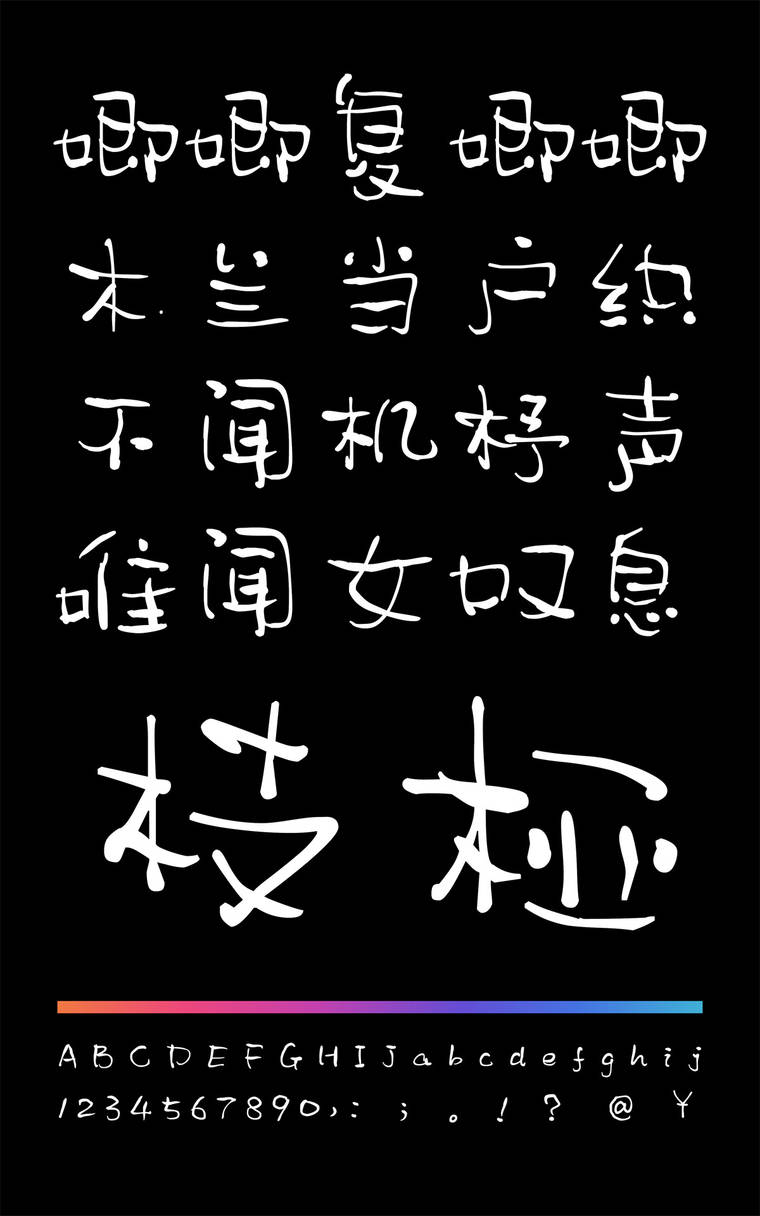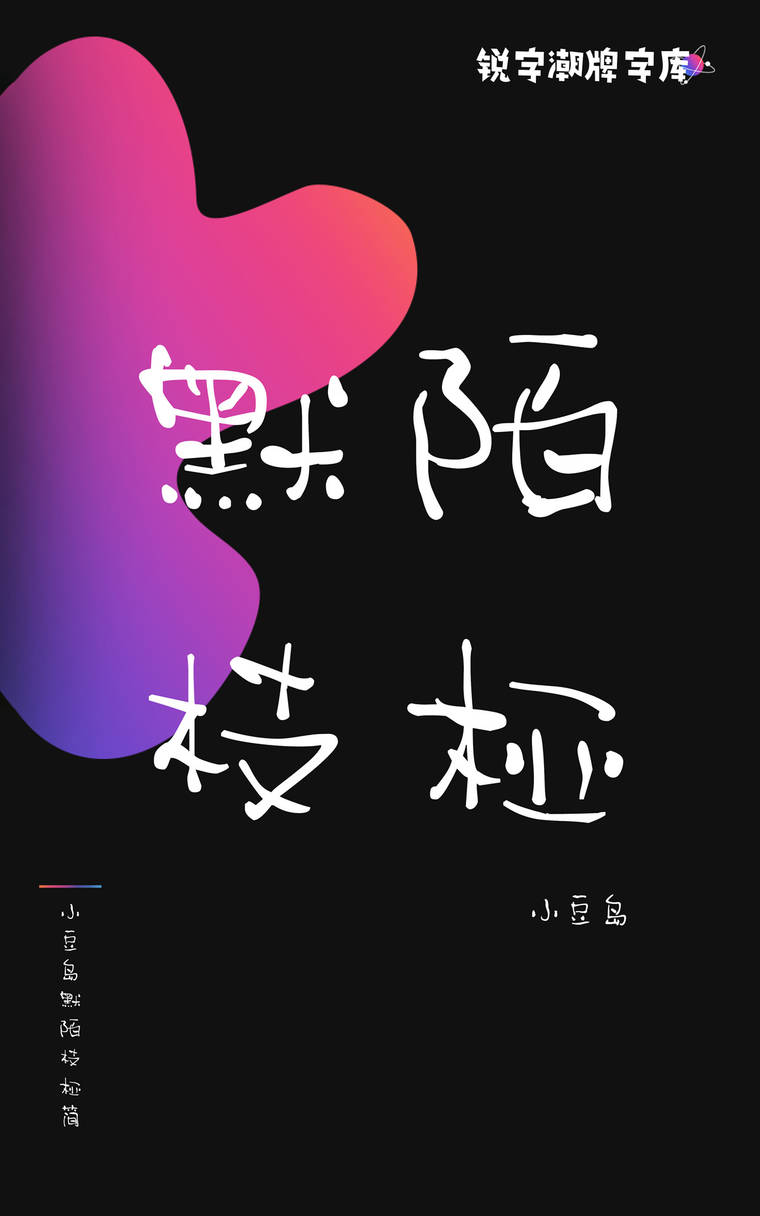
小豆岛默陌枝桠简
小豆岛默陌枝桠简,这款字体结构工整、笔画清晰,兼顾美观与易读性,适用于标题、正文、海报、包装、LOGO 等多种场景。字形优雅稳定,风格百搭耐看,适配日常排版与创意设计,让文字呈现更舒适、更具质感。小豆岛默陌枝桠简一笔一画,皆是细节,以均衡的比例、流畅的线条打造舒适视觉体验,字形端正大气,风格简约现代。无论是商业设计、品牌宣传还是日常排版,都能轻松驾驭,让文字更有格调与力量。小豆岛默陌枝桠简字体下载。
小豆岛默陌枝桠简字样展示
字体特征:疏密有致,触潇洒恣意,挥洒轻重缓急;有传统书法的写意,水墨书写风格,点划看似随意,却保持疏密有致,通过运笔节奏塑造线条粗细和节点,呈现出一种枯枝藤蔓的造型感,营造出清雅的禅宗意境
专业性:是一款独特水墨字体 字体整体风格统一的特点。应用性强,可以拉伸使用,线条富有节奏与灵气,灰度均匀,点缀生动,具有水墨特点。"